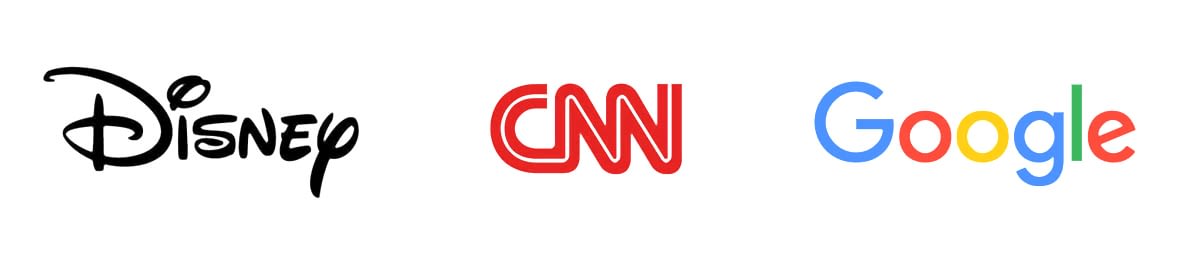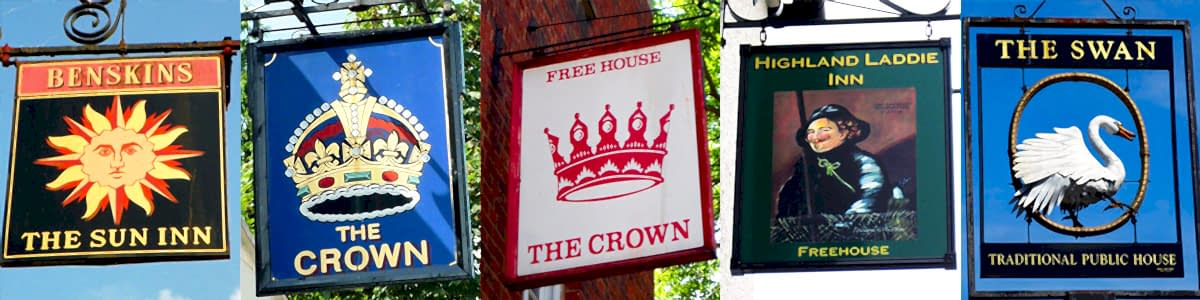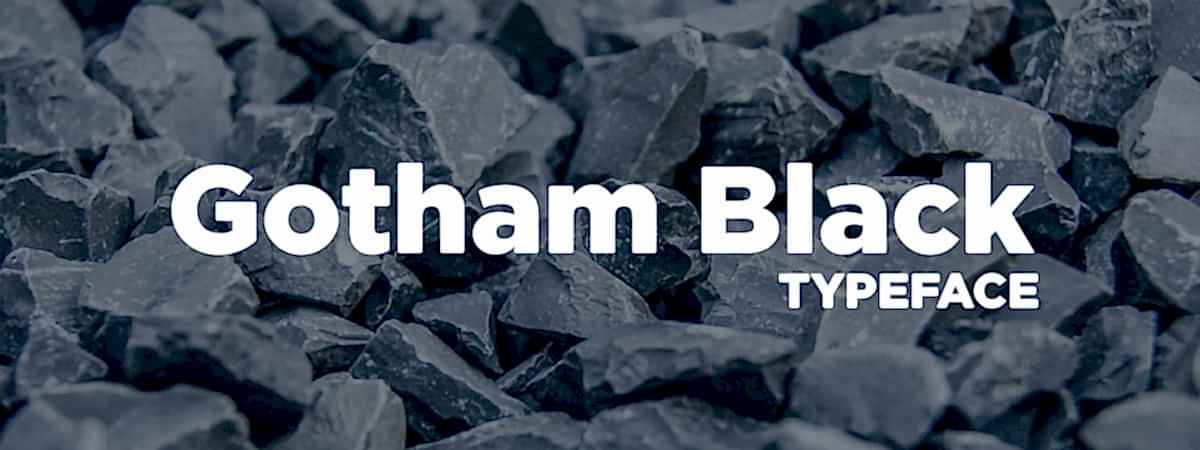
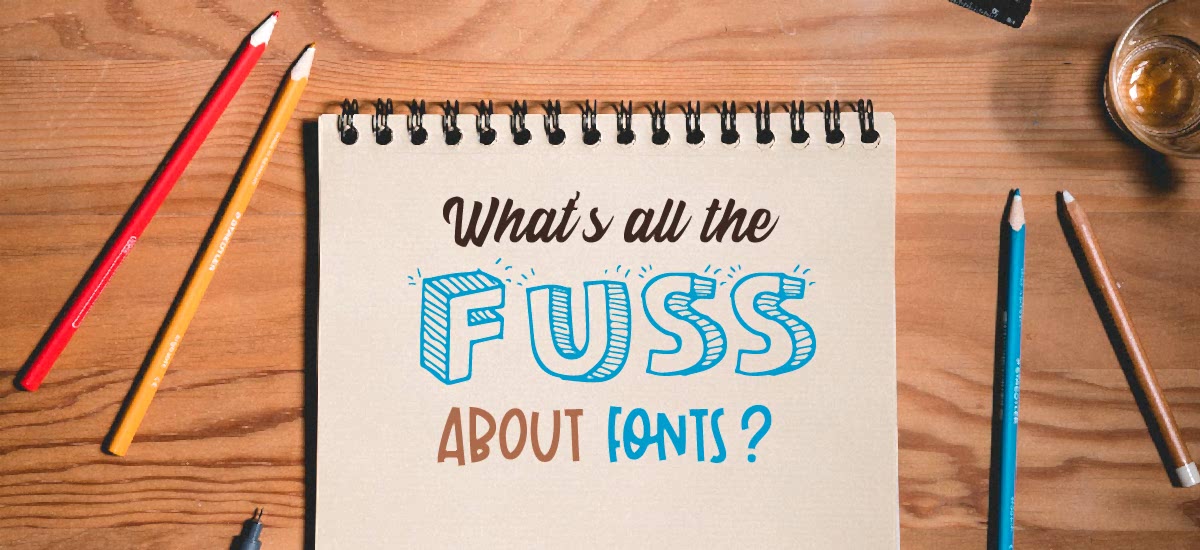
Seçtiğiniz yazı tipinin insanların mesajınızı nasıl yorumladığını etkilediği bir sır değil. Markanızın yüzü olması için mükemmel logoyu hazırlarken, logonuzdaki metin için seçtiğiniz yazı tipi (veya yazı tipleri!) çok önemlidir. Jenerik hissi veren bir yazı tipi sizi sıkıcı, unutulabilir bir logo ile baş başa bırakacak ve markanızla uyuşmayan bir yazı tipi de insanların kim olduğunuz ve sizden ne beklemeleri gerektiği konusunda kafalarının karışmasına neden olacaktır.
Peki siz kimsiniz? Ve ne yapıyorsunuz – ve bunu rakiplerinizden farklı olarak nasıl yapıyorsunuz? Kafanızda marka kişiliğinize dair net bir görüş yoksa, markanızla ilgili anahtar kelimeleri not etmek için birkaç dakikanızı ayırın. Markanızı nasıl tanımladığınızı ve hedef kitlenizin (ideal olarak!) onu nasıl tanımladığını düşünün. Aşağıdaki gibi anahtar kelimeler bulabilirsiniz:
Oyuncu, Sofistike, İlerici, Değer odaklı, Çevreye duyarlı, Geleneksel, Yaratıcı, Lüks, Güvenilir, Genç, Eski tarz, Erkeksi, Kadınsı, Alışılmamış...
Markanızın nasıl algılanmasını istediğinize dair net bir görüşe sahip olduğunuzda, logonuzda kullanacağınız en iyi yazı tipini kolayca belirleyebilirsiniz. Ve web sitenizde. Ve metin kullandığınız diğer her yerde. Bu nedenle, hangisinin markanıza en uygun olduğunu görmek için birkaç farklı yazı tipi kategorisine göz atın, ardından hangisinin en “size ”uygun olduğunu belirlemek için bu kategorideki yazı tiplerine yakından bakın.” Ama önce, yazı tiplerinin ve logoların tarihi hakkında konuşmak için hızlı bir yoldan gidelim.
Yazı Tipleri ve Logolar: Uzun Ömürlü Bir Çift
Fontun bir diğer adı da yazı karakteridir. Bu ifade Johannes Gutenberg'in matbaayı icat ettiği 1400'lü yıllara dayanmaktadır. Yazı karakteri”kelimesi tam anlamıyla hareketli yazı karakteri kullanılarak kağıda basılan tasarımı ifade eder. Gutenberg’in ilk yazı karakteri Blackletter olarak biliniyordu ve siz ’bunu – ve onu taklit eden modern yazı tiplerini – filmlerde, televizyonda ve “Orta Çağ”
gibi görünmek için tasarlanmış her şeyde kesinlikle görmüşsünüzdür.
Matbaanın icadı, modern yazı tipi kavramımızın başladığı yerdir. Önceleri tüm yazılı eserler elle yazılıyordu; yani bir bakıma her insanın el yazısı kendi kişisel yazı tipiydi. Ancak yazı tipi tasarımlarını standartlaştırmanın bir yolu yoktu, ta ki bunlar hareketli yazı bloklarına oyulup kitapların, gazetelerin ve diğer belgelerin binlerce aynı kopyasını basmak için kullanılana kadar. 1470 yılında Nicolas Jensen, antik Roma binalarında kullanılan tabelalardan esinlenen bir yazı karakteri olan Roman Type'ı icat etti. Ve sonra 1501'de Aldus Manutius dünyaya bugün hala kullandığımız bir yazı karakteri seçeneği sundu...italik.
Bugün, çok daha fazla seçeneğiniz var. Yazı karakterinizi kalınlaştırabilir, hızlı bir klavye kısayoluyla altını çizebilir, istediğiniz kadar büyük veya küçük yapabilirsiniz ve en önemlisi, indirip kullanabileceğiniz binlerce farklı yazı tipine sahipsiniz. Çoğu durumda, bunlar ücretsizdir.
Logolar, yazı tiplerinden biraz daha eskiye dayanır. Orta Çağ'da soylu aileler kendilerini armalarla tanımlıyorlardı. Bir armada renk şemaları, desenler, bazen hayvan figürleri ve ailenin sloganı ve/veya savaş çığlığı gibi metinler gibi tasarım öğeleri yer alırdı. Bir arma, onu taşıyan kişiyi derhal sembolle ilişkilendirilen ailenin bir parçası olarak tanımlıyor ve bu da onları markalaşmanın ilk örneklerinden biri haline getiriyordu
.
Orta Çağ'da ilerleyen logo ve markalaşma kavramları, İngiltere Kralı 2. Richard'ın tüm bira üreticilerinin kendilerini göze çarpan tabelalarla tanıtmalarını zorunlu kılan bir yasa çıkarmasıyla hız kazandı. Tavernalar tabelalarına hanedanlardan esinlenen resimler eklemeye başladılar ve bu da susamış müşterilerin kendilerini bulmalarına ve tanımalarına yardımcı oldu. Unutmayın, Ortaçağ Avrupa'sında çoğu insan okuma yazma bilmiyordu ve telefon da yoktu. Arkadaşınızla meyhanede bir şeyler içmek için buluşmak istiyorsanız, aynı meyhaneye gitmenizi sağlamanın en kolay yolu, Yeşil Ejderha meyhanesi veya Boar and Cock Pub gibi belirli bir meyhane tabelasında buluşmayı kabul etmekti.
Bu ilk logolar, markalarını tanımlamak için görüntülere ve renk şemalarına dayanıyordu ve bugünün logoları da farklı değil. Ancak günümüz logolarının cephaneliklerinde başka bir araç daha var: yazı tipleri. Böylece ejderha maskotunuzu yanıyormuş gibi görünen bir metinle eşleştirebilir veya lüks salonunuzun geometrik logosunu ince, zarif bir serif yazı tipiyle çerçeveleyebilirsiniz. Yazı tipi seçeneklerinizi görmeye hazır mısınız?
Serif Yazı Tipleri
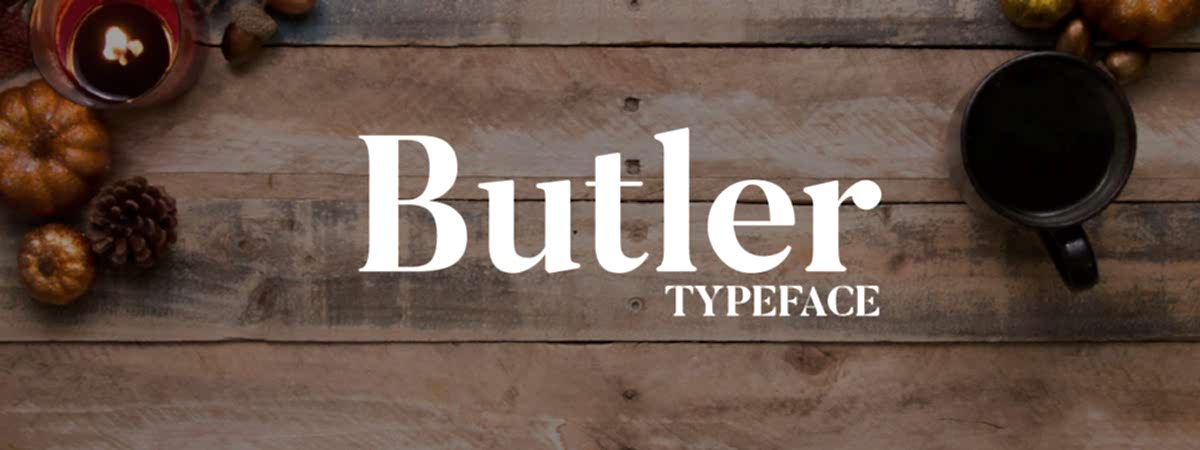
Serifler, belirli yazı tiplerindeki harflerin uçlarında ve köşelerinde bulunan küçük çıkıntılardır. En bilinen serifli yazı tiplerinden birkaçı Butler, Times New Roman, Georgia, Trajan Pro ve Baskerville'dir. Serifli yazı tipleri kullanan birkaç ünlü markaya bir göz atın ve bu markaları nasıl algıladığınızı düşünün.
Birkaç küçük çıkıntının bir yazı tipini gerçekten şık hissettirebilmesi ne kadar şaşırtıcı, değil mi? Serif yazı tipleri cilalı, lüks ve birçokları için eski tarz hissettiren markalar için tercih edilen yazı tipleridir. Zamansız, klasik markalar ve kendilerinin akıllı, sofistike bir seçim olduğunu anlatmak isteyen markaların fontlarıdır.
Sans Serif Yazı Tipleri
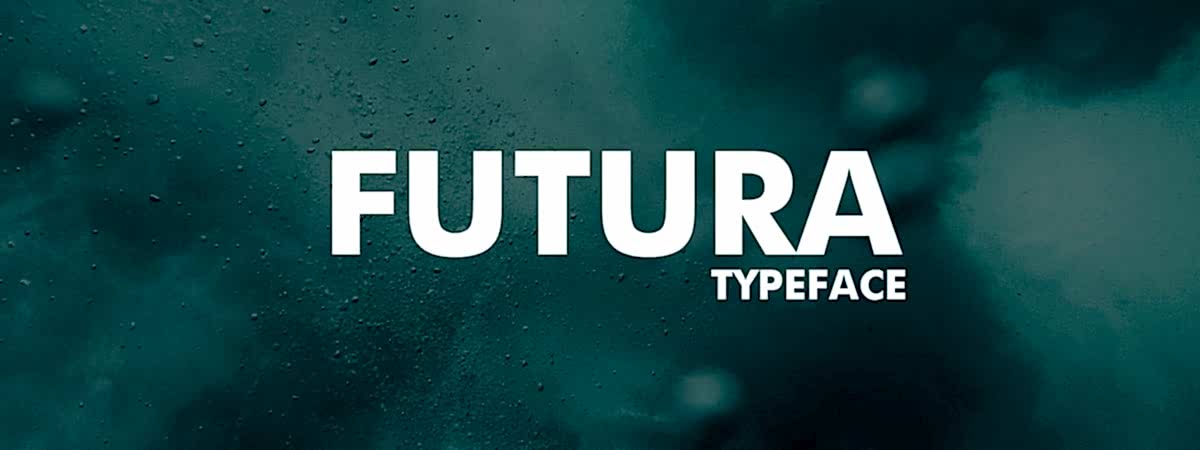
Adından da anlaşılacağı gibi, sans serif yazı tipleri serifleri olmayan yazı tipleridir. Bazı durumlarda, bir fontun bir serif ve bir sans serif versiyonu vardır, Liberation gibi.
Serif yazı tipleri geleneksel, gösterişli, zamansız markalar için mükemmel bir seçim olsa da, sans serif yazı tipleri modern, ilerici markalar için daha uygundur. Eğer bir teknoloji şirketiyseniz veya gençlere yönelik bir giyim mağazasıysanız, sans serif yazı tipini tercih edebilirsiniz. Benzer şekilde, rekabetin altını oymakla ve gösterişsiz hizmet sunmakla tanınan bir markaysanız, sans serif genellikle gidilecek yoldur. Futura, Eras bold, Helvetica, Arial ve Oldsans Black belki de en iyi bilinen sans serif yazı tipleridir.
El Yazısından Esinlenen Yazı Tipleri
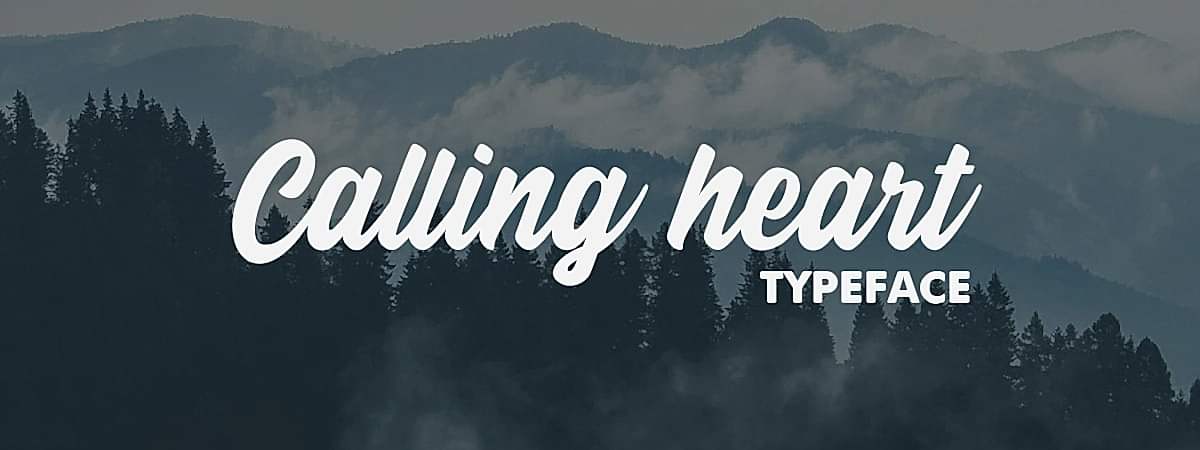
Adından da anlaşılacağı gibi, el yazısından esinlenen fontlar elle yazılmış gibi görünen fontlardır. El yazısından esinlenen yazı tipleri, organik ve ev yapımı hissi veren her marka için mükemmel bir seçimdir. Ayrıca, işiniz ne kadar büyük olursa olsun, yaptığınız her şeye kişisel dokunuşunuzu kattığınızı dünyaya göstermenin etkili bir yoludur.
El yazısından esinlenen yazı tipleri çeşitli stillere sahiptir; bazıları hayali bir yazı gibi görünürken, diğerleri yapışkan bir kağıda not alınmış gibi görünür. Tıpkı bir kişinin kişisel el yazısından onun hakkında çok şey anlayabileceğiniz gibi, dünya da seçtiğiniz el yazısından ilham alan yazı tipinden markanız hakkında çok şey anlayabilir. Ünlü el yazısı fontları arasında Calling heart, Qlassik Bold, Androgyne, Tibitha ve Sweaty yer alır.
Kalın (Ve O Kadar da Kalın Olmayan) Yazı Tipleri
Cesur, yüzünüzü gösteren bir marka mısınız? Evet mi? O zaman – mesajınızı CESUR bir yazı tipiyle stratosferin ötesine haykırın.
Kalın ve cesur bir yazı tipi, markanızın hesaba katılması gereken bir güç olduğunu tüm dünyaya gösterir. Yer kaplarsınız, geri adım atmazsınız. Kalın bir yazı tipi, bir rock mekanı, bir zipline kursu, bir kişisel antrenör veya hatta baharatlı atıştırmalıklar serisi gibi yüksek enerjili, yüksek yoğunluklu herhangi bir marka için ideal seçimdir. Gotham Black, Cunia, Oswald, Cornerstone gibi fontlar işinizi görecektir!
Bu mutlaka agresif olduğunuz anlamına gelmez, ancak itilip kakılmayacağınız ve görmezden gelinemeyeceğiniz anlamına gelir. Buna karşılık, ince, silik bir yazı tipinin onu seçen marka hakkında ne söylediğini düşünün.
İnce bir yazı tipi daha sakin, daha sessiz hissettirir, ancak daha az güçlü olması gerekmez. Bunun nedeni, yazı tipi tasarımlarının incelikli olması ve harflerin ağırlığının nasıl dağıtıldığı, yazı tipinin serifli olup olmadığı ve harflerin köşeli mi yoksa yuvarlak mı olduğu gibi görünüşte küçük olan her tasarım öğesinin, markanızın bir yönünü onu görüntüleyen insanlara iletebilmesidir.
Vintage Esintili Yazı Tipleri
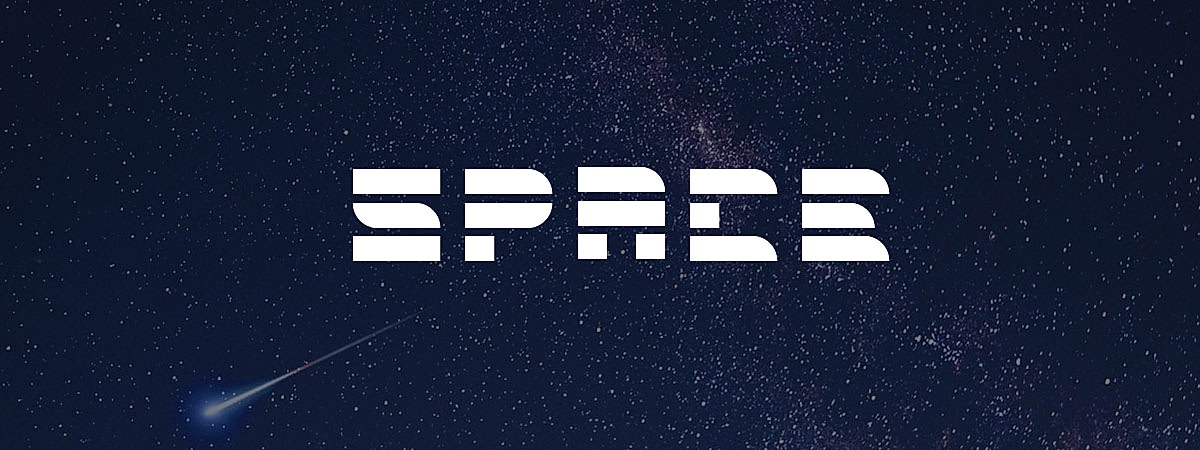
Eğer vintage kıyafet satıcısı veya tarihi canlandırma grubu gibi retro esintili bir markaysanız, vintage esintili bir yazı tipi sizin için bir seçimdir.
Vintage yazı tipleri sadece vintage markalar için değildir. İşleri eski moda yöntemlerle yaptıklarını vurgulamak isteyen her marka için etkili bir seçimdir. Vintage esintili bir yazı tipi kullanmak, markanıza güven duygusu aşılayabilir ve onu köklü, güvenilir bir seçim gibi hissettirebilir.
Diyelim ki bir teslimat servisisiniz. Eski moda görünen bir yazı tipiyle, potansiyel müşterilere sizinle bir araba rezervasyonu yaptıklarında, yüksek kaliteli, eski moda müşteri hizmetleri bekleyebileceklerini ince bir şekilde gösterirsiniz. Müşteri hizmetlerinin geçmişte gerçekten daha iyi olup olmadığı burada önemsizdir – müşterileriniz öyle olduğuna inanırsa ve onlara hızlı, kibar hizmet sunmak gibi eski moda değerlere sahip olduğunuzu iletirseniz, bu tür bir deneyim arayan müşteriler aynı sözü vermeyen bir marka yerine size gelecektir.
Vintage esintili yazı tipleri, özellikle kitschy, campy hissi veren tuhaf markalar için de eğlenceli bir seçimdir.
Novelty Fonts
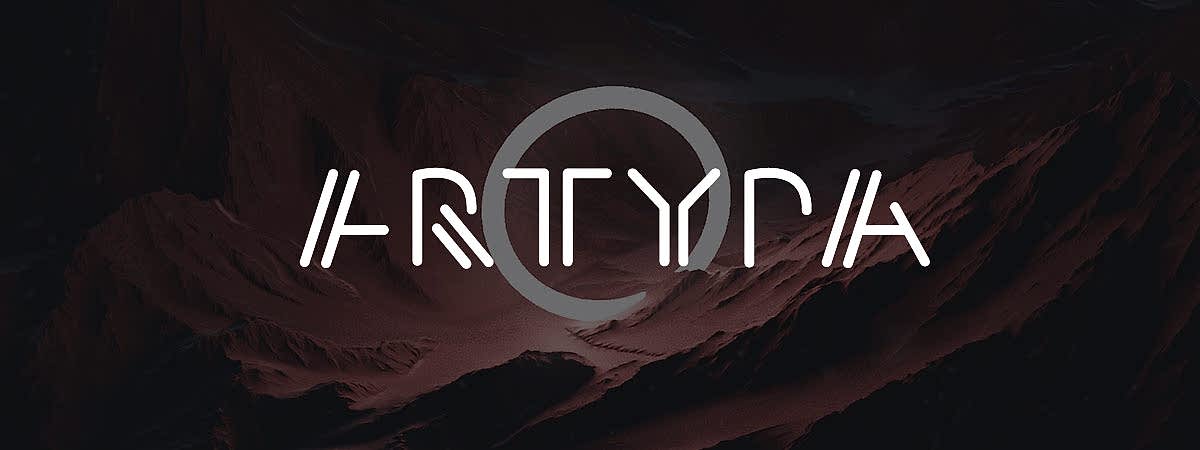
Ve bir de sadece eğlenceli olan fontlar var. Bunlar ilginç, tuhaf, alışılmadık ve diğer yazı tiplerine hiç benzemeyen yazı tipleridir. Diğer yazı tiplerine benzememek burada bir hata değil... bu bir özelliktir.
Eğer süper benzersiz bir markanız varsa, süper benzersiz bir yazı tipiyle ucube bayrağınızın dalgalanmasına izin verin. Aslında, özel bir yazı tipine yatırım yapmak bile isteyebilirsiniz, böylece sahip olduğunuz yazı tipini kullanan tek marka siz olursunuz.
Yeni bir yazı tipi kullanmanız için markanızın çok sıra dışı olması gerektiğini düşünmeyin. Tuhaf ve eğlenceli olan herhangi bir marka, hayatı çok ciddiye almadıklarını anlatmak için eğlenceli veya tuhaf bir yazı tipi kullanabilir.
Logonuz için Doğru Yazı Tipini Bulma
Bir marka olarak tam olarak kim olduğunuzu net bir şekilde anladığınızda, logonuzda kullanmak için mükemmel yazı tipini seçmek kolaydır.
Peki ya markanızı tanımlayan anahtar kelimeler tek bir kategoriye girmiyorsa? Yalnız değilsiniz – her marka kendine özgü özelliklerin bir karışımıdır, bu nedenle eğlenceli ve sofistike veya lüks ve büyük bir değer sunmaya odaklanmış olmak tamamen mümkündür. Markanızın tüm yönlerini bir yazı karakterinde birleştiren bir yazı tipi bulun.
Örneğin, diyelim ki geleneksel yetiştirme, muhafaza etme ve stoklama yöntemlerini benimseyen, ilerici düşünen bir sağlıklı gıda mağazaları zincirisiniz. Plastik atıkları azaltmak için tüm meyve ve sebzeleri kutulara koyan ve küçük partiler halinde teneke kutularda ve cam kavanozlarda konserve ürünler sunan bir organik ürün pazarı düşünün. Bu marka için ideal yazı tipi, Lemon Yellow Sun veya Norquay gibi el yazısından esinlenen sans serif bir yazı tipi olabilir.
Bu gibi fontlar dafont.com veya 1001fonts.com gibi çevrimiçi veritabanlarında bulunabilir. Bazı durumlarda, bir fontu kullanmak için lisans satın almanız veya yaratıcısından izin almanız gerekir.
Logo Oluşturmak için Yazı Tipleri Nasıl Kullanılır
Tüm logolar bir resimle eşleştirilmiş metinlerden oluşmaz. Bazıları sadece bir şirketin adı veya baş harflerinden oluşur. Bu tür logolara kelime işareti logosu denir ve bunların en ünlüsü muhtemelen Disney logosudur.
Markaların kelime işareti logolarını seçmelerinin birçok nedeni vardır. Yaygın nedenlerden biri, markanın ayırt edici bir isme sahip olması ve bu ismi markalaşmasında ön plana çıkarmak istemesidir. Bu aynı zamanda gelecek vaat eden markalar için de yaygın bir markalaşma stratejisidir, çünkü markanın ismini logolarının odak noktası haline getirmek, isimlerini tanınır hale getirmenin ve (ideal olarak) girişimlerini ev isimlerine dönüştürmenin hızlı bir yoludur.
Bir wordmark logosunda, hangi yazı tipini kullanacağınız en önemli tasarım seçimidir. Nedeni basittir – logonuzun tamamı metindir, bu nedenle yazı tipiniz zayıfsa onu taşıyacak bir görüntü yoktur. Yazı tipi seçerken aklınızda bulundurmanız gereken birkaç önemli noktayı aşağıda bulabilirsiniz:
• Bir yazı tipinin karakter aralığına, yani harfler arasındaki boşluk miktarına çok dikkat edin. Bazı yazı tiplerinde harfler arasında çok az boşluk vardır, bu da okunmalarını zorlaştırabilir
• Markanızı en iyi hangi şekillerin tanımladığını düşünün. Tıpkı renk ve yazı tipi gibi, logonuzdaki şekiller de marka kişiliğinizi ifade eder. Daireler ve diğer yuvarlak şekiller daha arkadaş canlısı, daha yumuşak bir markayı ifade ederken, kareler ve köşeli şekiller daha muhafazakar, daha mesafeli bir kişiliği ifade eder. Markanız için hangilerinin uygun olduğunu belirlemek için düşündüğünüz her yazı tipindeki harflerin şekillerine bakın
• Yazı tipi, kullanmayı planladığınız boyutlarda okunabilir olmalıdır. Bunu bir yazı tipi seçerek test edin, ardından okumanın zorlaştığı noktayı görmek için boyutlandırın. Genel olarak, daha ince ve karmaşık yazı tiplerinin küçük boyutlarda okunması zorken, daha kalın ve baskı tarzı yazı tipleri küçültüldüklerinde okunaklı kalırlar
Marka adınızla nasıl göründüklerini görmek için yazı tiplerini test etmek gerçekten çok kolay. Eğer logo maker like Logogenie’s kullanıyorsanız, araca markanızın adını yazın ve açılan yazı tipi listesinden seçiminizi yapın. Hatta devam eden logonuza aynı anda iki metin bloğu ekleyebilir ve markanızın adı için farklı yazı tiplerini yan yana karşılaştırabilirsiniz. Logogenie’nin logo oluşturucusu ayrıca yazı tipinizi yukarı ve aşağı boyutlandırma ve her harf arasındaki boşluk miktarını artırma veya azaltma seçeneği sunarak yazı tipinizin karakterizasyonu üzerinde kontrol sahibi olmanızı sağlar.
Doğru Yazı Tipi ile Mesajınızı Netleştirin
Markanız için mükemmel yazı tipini bulmaya hazır mısınız? Markanızı benzersiz kılan her şeyi mükemmel bir şekilde harmanlayan yazı tipini bulmak için çevrimiçi yazı tipi veritabanlarından herhangi birine göz atın. Sizinki gibi markaların kullandığı yazı tiplerine göz atmak da harika bir fikir. Kendinizi rakiplerinizle sınırlamayın; kim olduklarını ve neyle ilgili olduklarını anlatmak için fontları nasıl kullandıklarını görmek için sizinkine benzer değerlere sahip herhangi bir markaya göz atın
.
Ayrıca, grafik tasarımcınızın doğru yazı tipini seçmenize yardımcı olma becerisini de hafife almayın. Profesyonel bir tasarımcı olarak, markaları yazı tipleriyle eşleştirme ve müşterilerinin marka kişiliklerini görsel tasarım seçimleriyle ifade etme konusunda deneyim sahibidirler.
Peki ya bir grafik tasarımcı ile çalışmıyorsanız?
Ya da sahip oldukları binlerce font arasından mükemmel olanı bulmak için font veritabanlarında gezinecek vaktiniz yoksa?